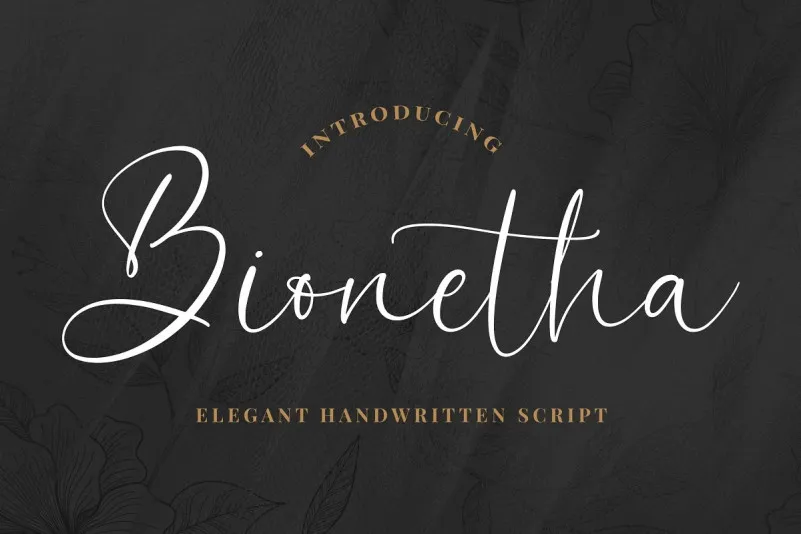
Bionetha Font – Fonte Grátis
Bionetha Font
A Bionetha Font é uma elegante script feminina, cuidadosamente desenvolvida para se tornar uma escolha favorita. Esta font foi criada a partir de escritas manuscritas no papel, posteriormente digitalizadas e redescrita em formato vetorizado com precisão meticulosa. Seu design moderno e delicado é perfeito para qualquer projeto que deseja dar um toque diferenciado, seja ele uma capa de livro, cartões de aniversário ou até mesmo marcas de estudo. Com sua textura única e seu charme suave, a Bionetha é uma escolha ideal para aquelas pessoas que buscam uma fonte elegante para destacar em seus trabalhos digitais. Se você está procurando por uma fonte que não apenas destaca em um projeto particular, mas também se torna um recurso confiável e versátil à medida que sua carreira evolui, a Bionetha Font pode ser a escolha certa.